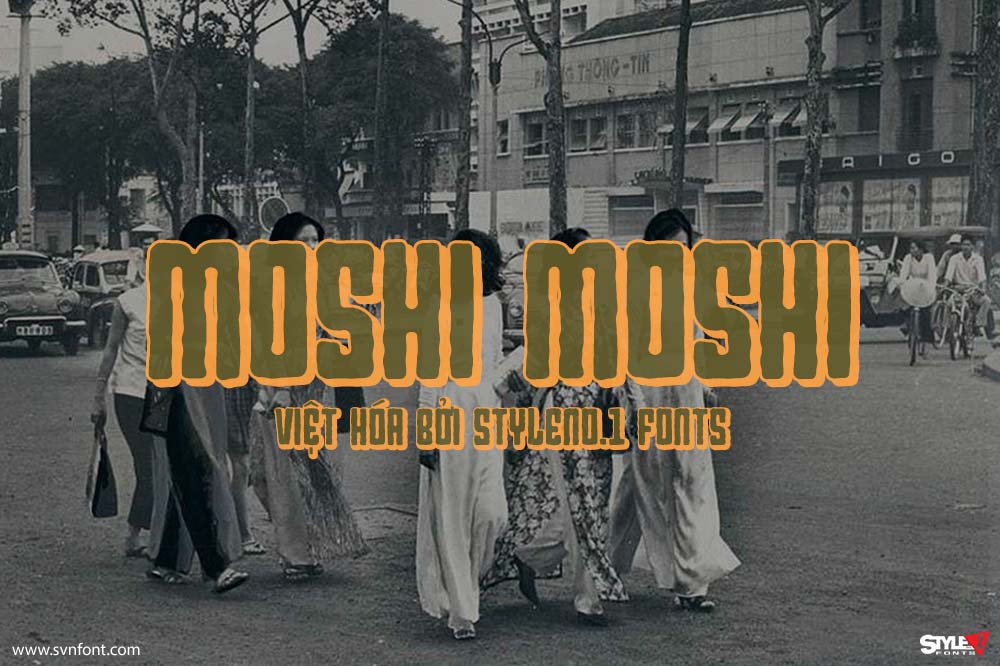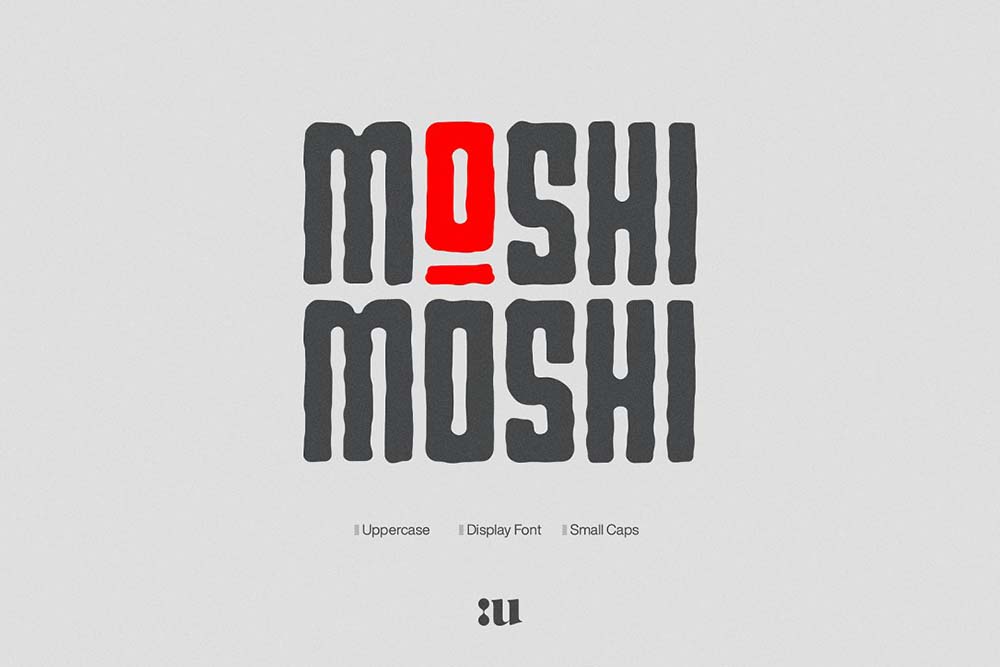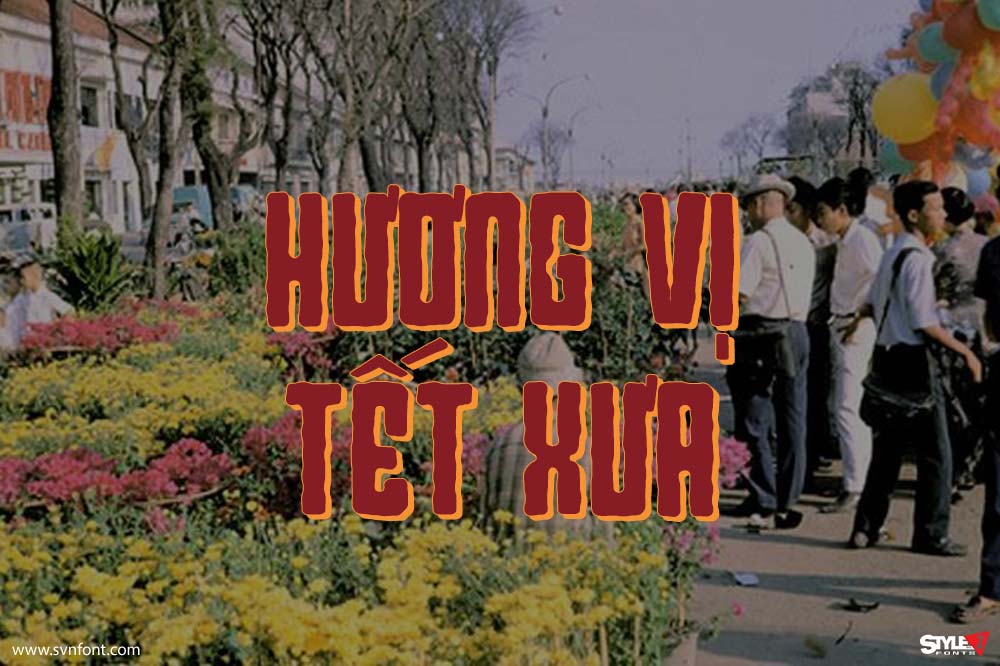
Font Việt Hóa SVN - Moshi Moshi Mang Phong Cách Hiện Đại, Tối Giản
Lấy cảm hứng từ những tấm áp phích đường phố Nhật Bản, kiểu chữ tạo khối hoàn toàn bằng chữ hoa này mang đến sự hiện đại. cảm hứng từ nghệ thuật vẽ tay đường phố của Nhật Bản, “Moshi Moshi” có các dạng chữ thô, nhưng đồng thời truyền tải một phong cách hiện đại và tối giản.
Nhà thiết kế: Bruno Pierini
Nhà phát hành: Unio
Việt hóa: STYLEno.1 Fonts